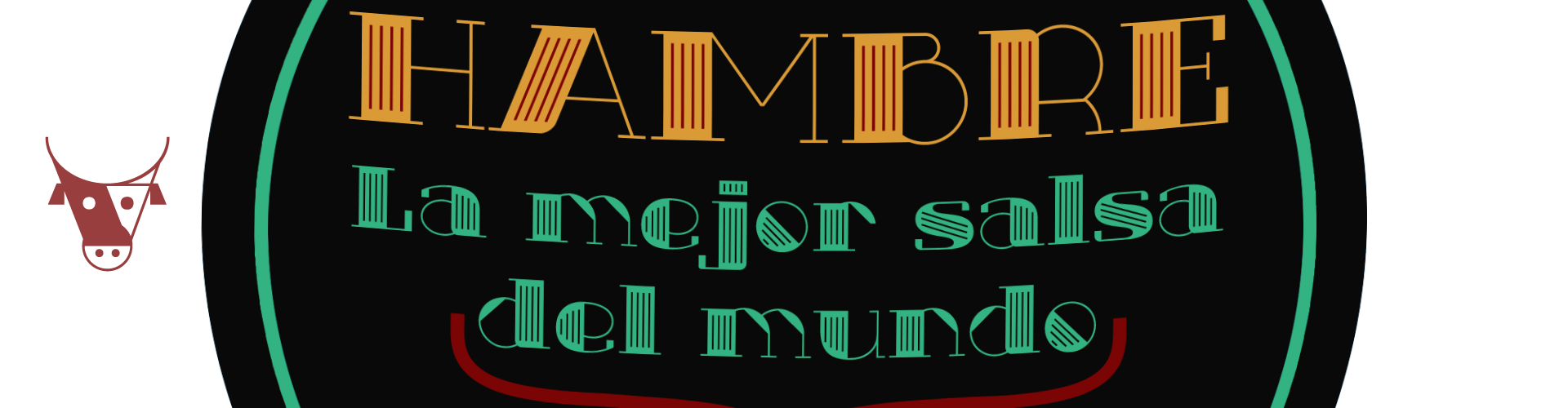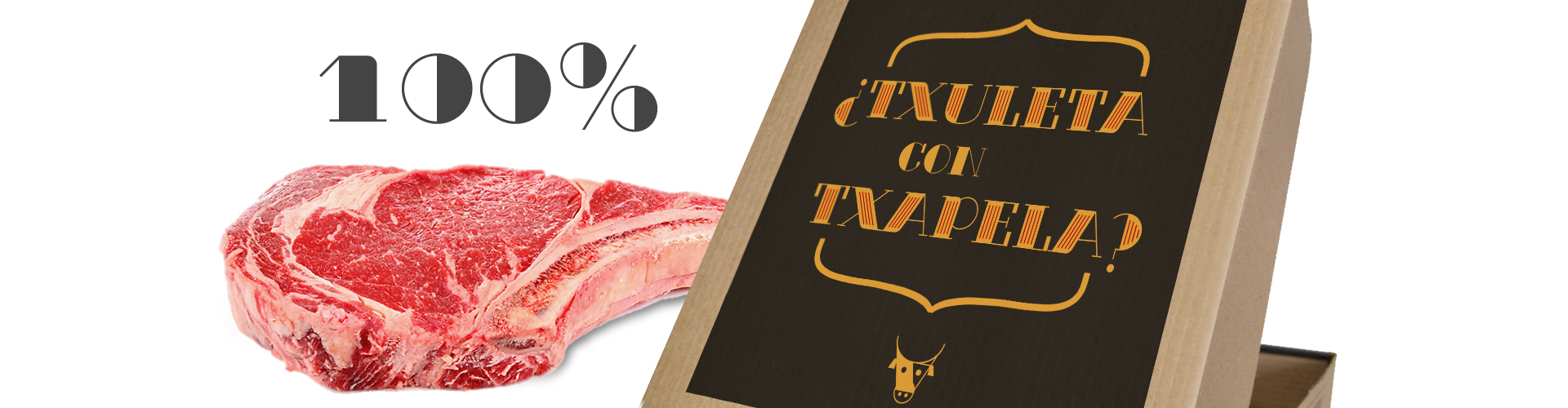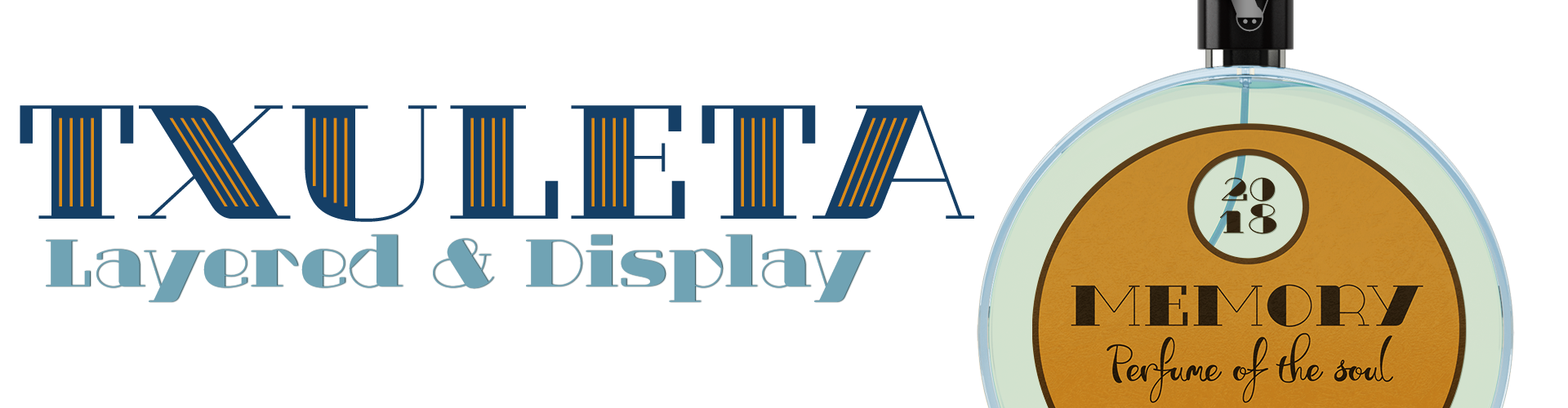
Layered & Display
Estilo: Modernista, Serif, Decorativa, Layered, Didona, Display
Proporción: Regular, Deco & Lines
La tipografía se compone de 3 estilos combinables por capas para crear titulares tipográficos multicolores.
Txuleta incluye letras alternativas para algunas mayúsculas y minúsculas, números estilo antiguo, el símbolo del Bitcoin (
b#), otros símbolos monetarios. y funciones avanzadas OpenType.